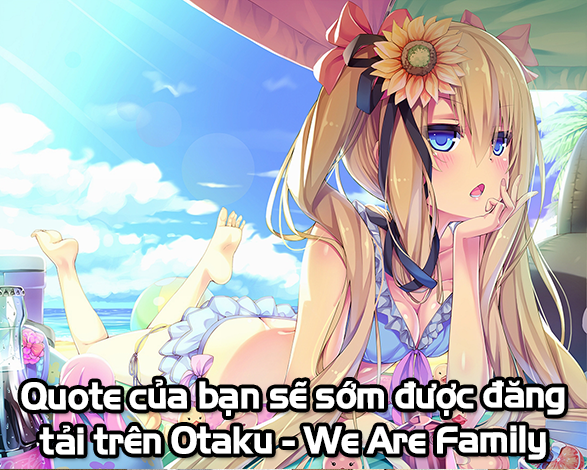
Các bác cho em xin tên font này ạ
Giúp mình với
Ai giúp mình với căng với font này quá
kyukool Breath Pro ( deu la glyph di kem dc cat va ve lai )
Mọi người cho mình hỏi font chữ thegioididong.com là font j vậy, mình thử hết tất cả các font chữ trong máy mà tìm không thấy :(
Bác nào có font Helvetial Nueu CE-Bold cho em xin với, em tìm hoài ma không thấy T.T, chân thành cảm ơn!
[​IMG][/IMG] thanks bác, Đã thử rồi mà vẫn không được bác :( HelveticaNeueCE-Bold, font này tìm hoài không ra
Bạn nào giúp mình font này với ạ!
ĐC cái nài hay cái đó./
bạn tìm ra font này chưa cho mình thông tin với. Thanks
Mình hỏi them cái. Mình tìm được fonts là (Sloop Script Bold Two) nhưng không thể gõ được các chữ cái ư Ơ ô ...vv bạn có thể hướng dẫn mình sử dung được không> thank!
Kanzz.Elf chưa bác ơi, vẫn đang chờ đây
có ai biết Font của "Em làm sao" là gì không ạ?
Cho em hỏi đây là font gì ạ, nhìn đẹp quá trời :*
mọi người cho mình hỏi font này là font gì vậy? nó khá giống font Thời Đại nhưng lại k phải :( chứ R của bên Thời Đại thì k có dấu mốc